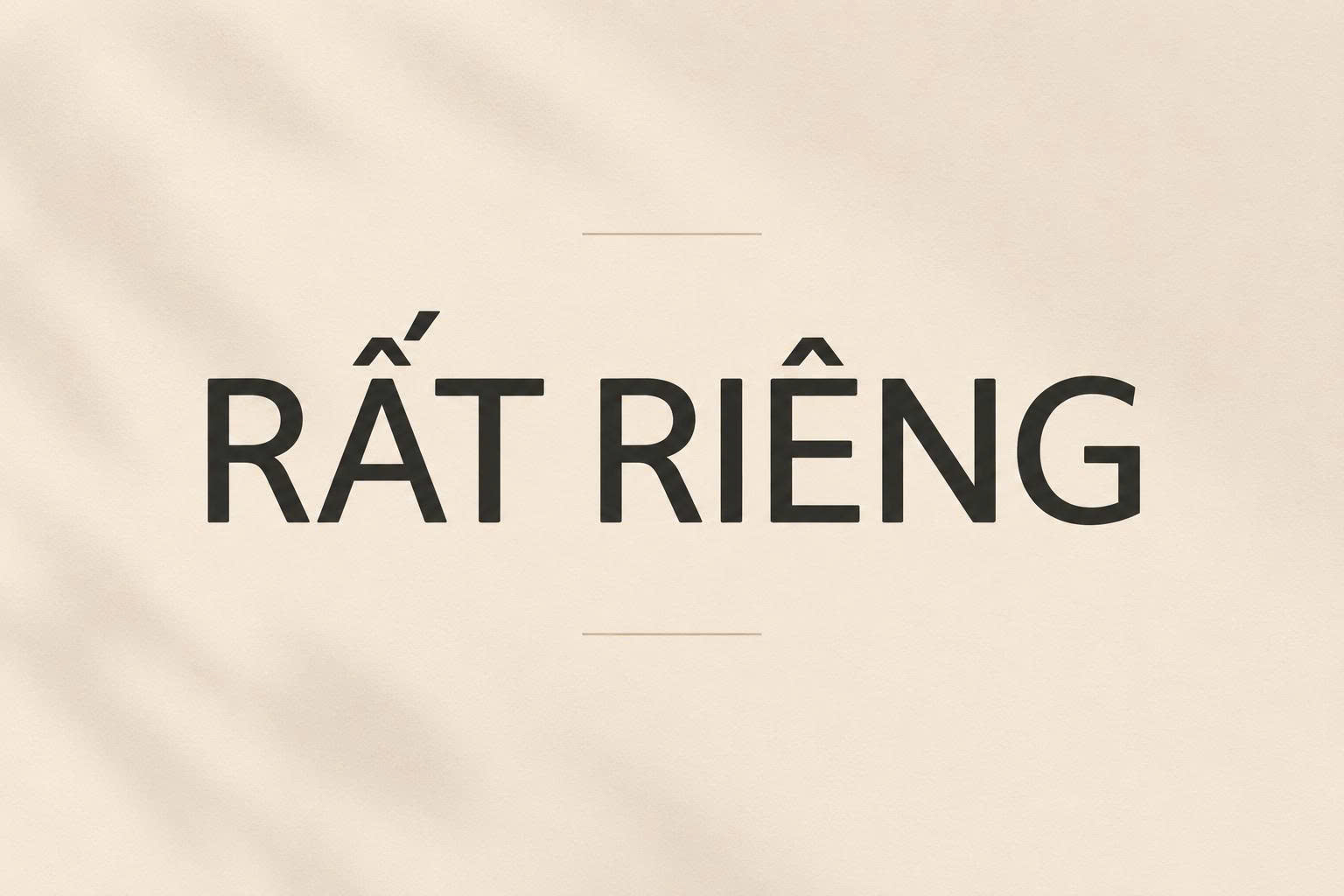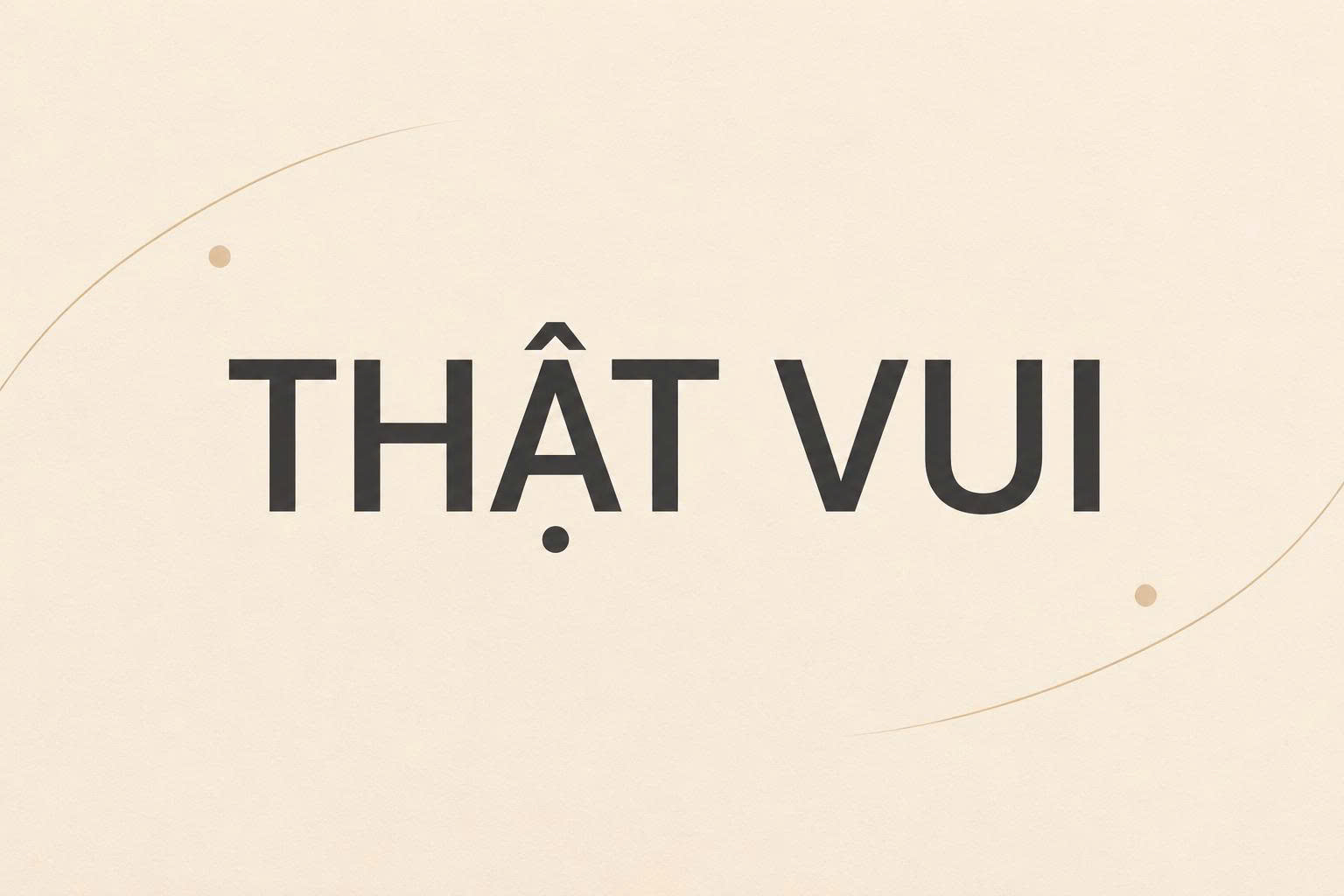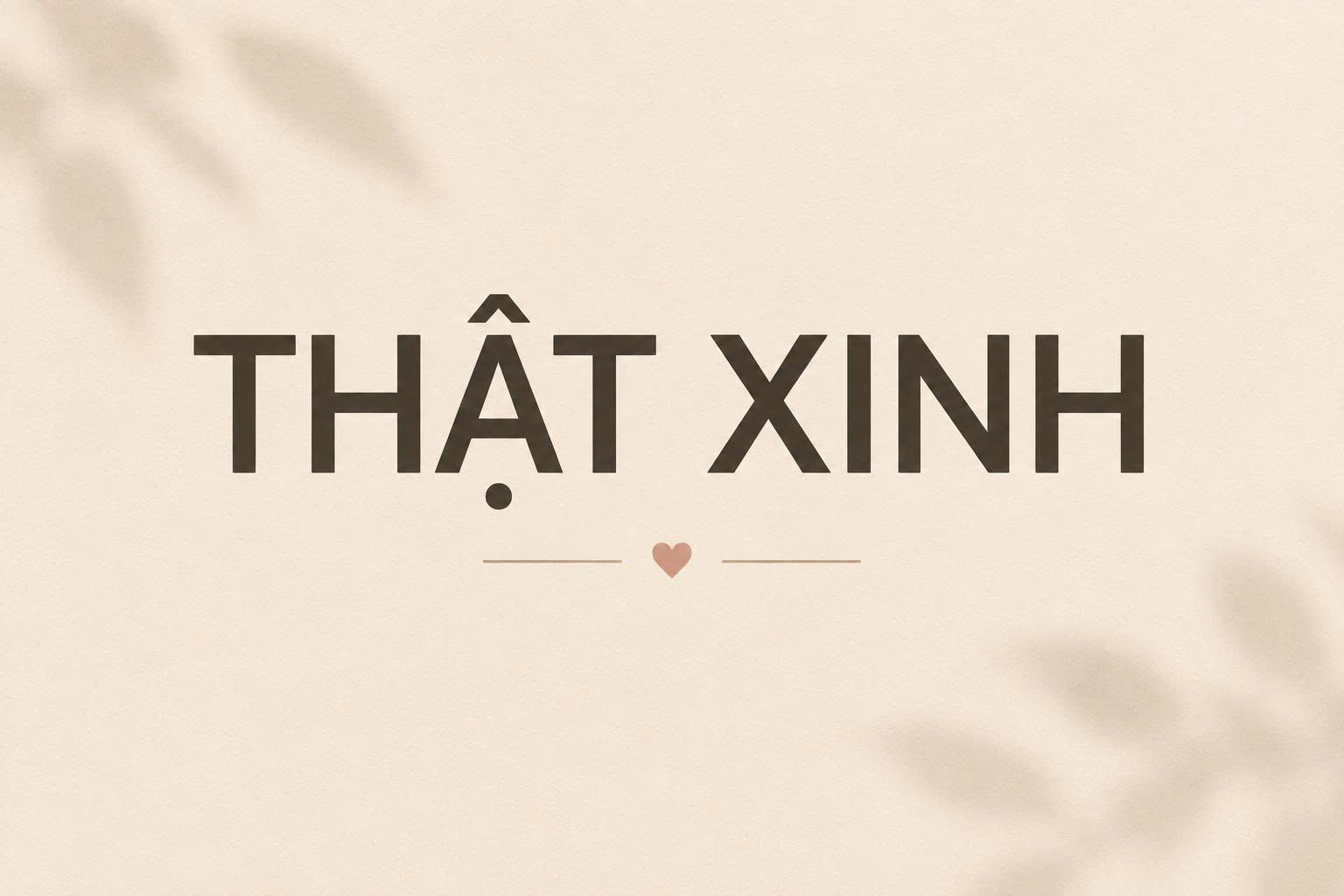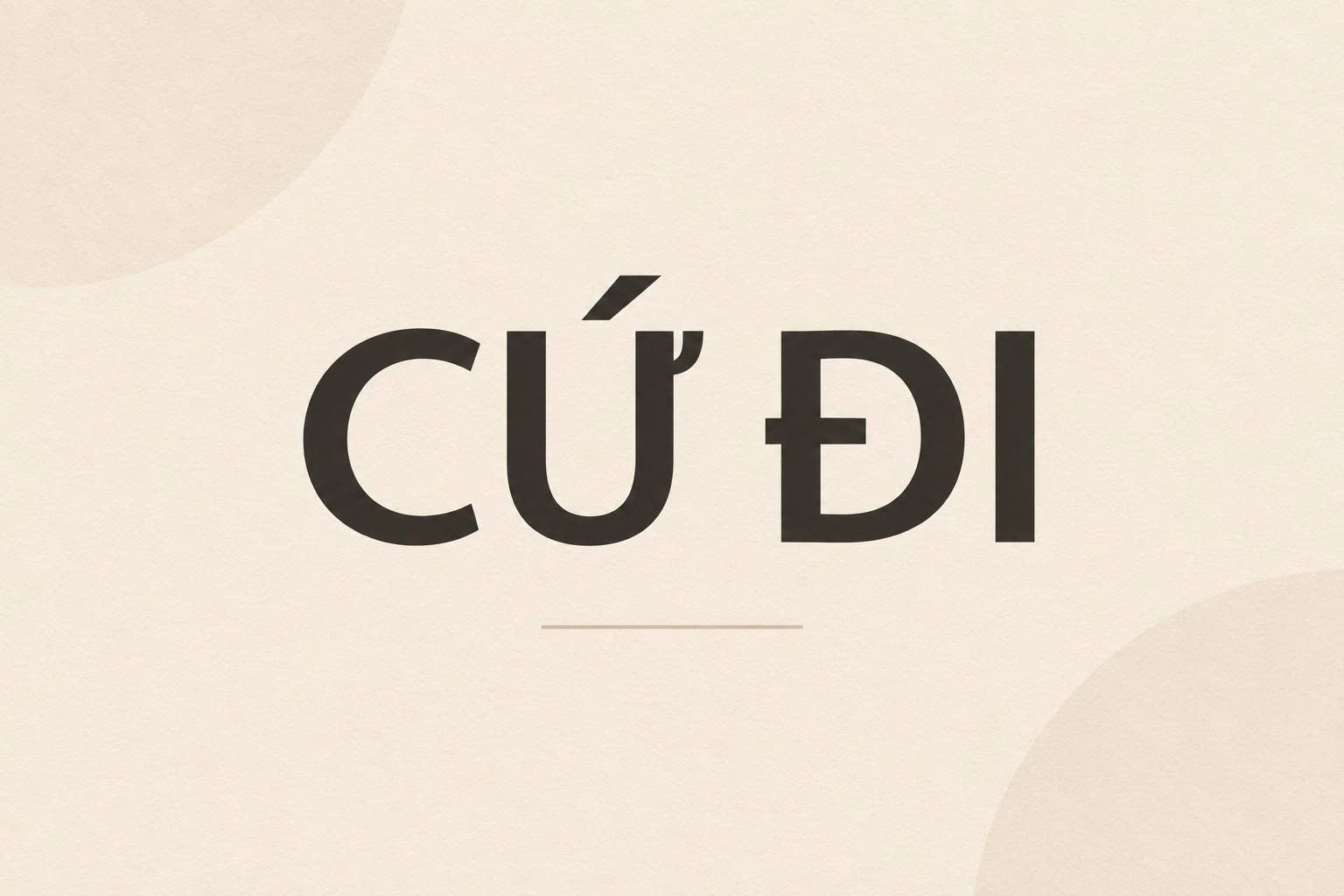
Download font Myriad Pro là nhu cầu hàng đầu của các designer khi cần một bộ phông chữ không chân (Sans-serif) hiện đại, chuyên nghiệp và có tính ứng dụng cực cao. Được thiết kế bởi Robert Slimbach và Carol Twombly cho Adobe, Myriad Pro nổi tiếng với cấu trúc chữ Humanist sạch sẽ, dễ đọc và là lựa chọn kinh điển cho các bộ nhận diện thương hiệu lớn toàn cầu. Doozypack.vn chia sẻ link tải font Myriad Pro Việt hóa trọn bộ, giúp bạn sở hữu phông chữ chỉn chu để thiết kế bao bì, logo và website mà không gặp bất kỳ lỗi hiển thị dấu tiếng Việt nào.
Đặc điểm thiết kế vượt trội của bộ font Myriad Pro
Myriad Pro không chỉ đơn thuần là một phông chữ hiện đại; nó là kết quả của sự tối ưu hóa trải nghiệm thị giác, mang lại sự cân bằng giữa nghệ thuật và công năng.
Phong cách Humanist Sans-serif thân thiện
Đặc trưng lớn nhất của font Myriad Pro là cấu trúc chữ mở rộng với các nét vẽ dứt khoát nhưng vẫn có độ cong mềm mại tự nhiên. Thiết kế này mang lại cảm giác vô cùng minh bạch, trung tính và chuyên nghiệp. Nhờ khoảng hở trong chữ (counter) được tính toán tỉ mỉ, Myriad Pro giúp người đọc nhận diện ký tự nhanh chóng, giảm thiểu tình trạng mỏi mắt khi theo dõi các khối văn bản dài trên catalogue hay mặt sau hộp giấy.
Hệ thống biến thể phong phú cho thiết kế chuyên nghiệp
Một lý do quan trọng để bạn tải font myriad pro chính là hệ sinh thái biến thể vô cùng đồ sộ. Từ các bản Light thanh mảnh đến download font myriad pro bold mạnh mẽ, hay các bản Condensed tiết kiệm diện tích. Sự đa dạng này cho phép designer dễ dàng thực hiện quy tắc phân cấp thị giác (Hierarchy) trên bao bì sản phẩm, giúp khách hàng nhận diện nhanh thông tin quan trọng nhất.
Tại sao designer cần tải font Myriad Pro Việt hóa?
Trong ngành thiết kế đồ họa tại Việt Nam, việc sử dụng phiên bản Việt hóa chuẩn mang lại những lợi ích thiết thực cho quy trình sản xuất bao bì tại Doozypack.vn:
- Giải quyết triệt để lỗi nhảy dấu: Việc download font myriad pro việt hóa chuẩn đảm bảo các ký tự như “ơ, ư, đ” hay các dấu thanh không bị lỗi hiển thị ô vuông, giữ nguyên ý đồ thiết kế ban đầu.
- Tính chuyên nghiệp cao: Các bộ dấu trong bản Việt hóa tại Doozypack.vn được tinh chỉnh hài hòa với độ dày nét chữ, giúp văn bản tiếng Việt luôn cân đối và đẳng cấp.
| Biến thể Font | Đặc điểm thị giác | Ứng dụng đề xuất tại Doozypack.vn |
| Myriad Pro Regular | Cân đối, dễ đọc | Dùng cho nội dung mô tả, bảng thành phần (Body text). |
| Myriad Pro Bold | Vững chãi, nổi bật | Dùng làm tiêu đề phụ, tên sản phẩm hoặc logo thương hiệu. |
| Myriad Pro Condensed | Hẹp, tiết kiệm diện tích | Dùng cho nhãn dán chai lọ nhỏ hoặc các thông số kỹ thuật. |
Gợi ý lựa chọn: Nếu bạn cần trình bày nhiều thông tin kỹ thuật trên một mặt tem nhãn hẹp, hãy ưu tiên sử dụng biến thể Myriad Pro Condensed. Biến thể này giúp bạn hiển thị nhiều nội dung hơn mà không cần giảm kích thước chữ xuống quá nhỏ gây khó đọc cho người dùng.